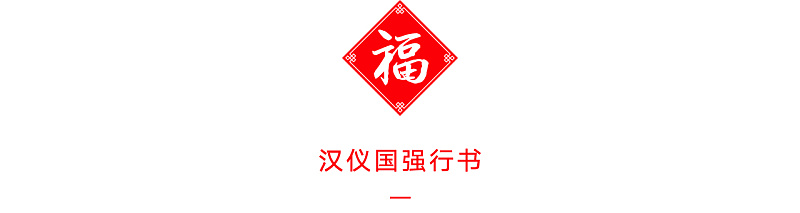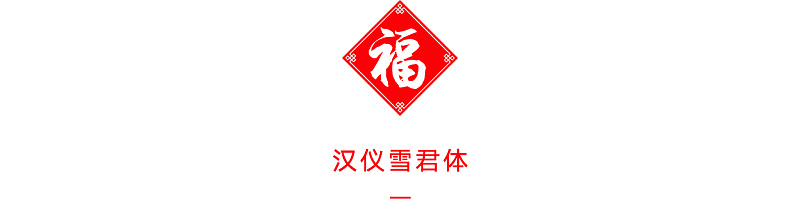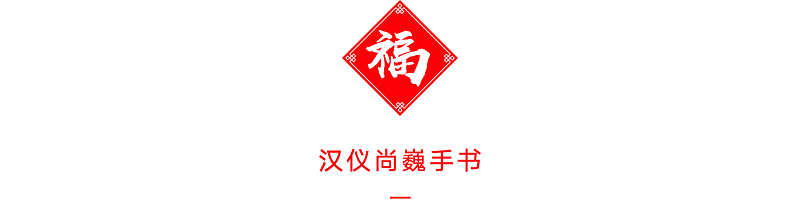
汉仪新品书法体|喜气洋洋的新年问候!
到了年关,没几款书法字体备用,设计师都没法开工了。
为什么人人都爱书法体?!
潇   洒
/
磅   礴
/
有气势
市面上的书法字众多,可不要迷失在茫茫笔刷中,
今天小编为大家带来9款高品质书法体,
同大家一起感受下来自汉仪书法字体的喜气问候吧!
柔软饱满,任情意挥洒!
文人行书,潇洒有内涵!
丰盈流畅,饱满有福气!
师者风范,潇洒俊逸感!
霸气抢眼,有超强气场!
清新行书,莘莘学院风!
释放真我,活泼有力量!